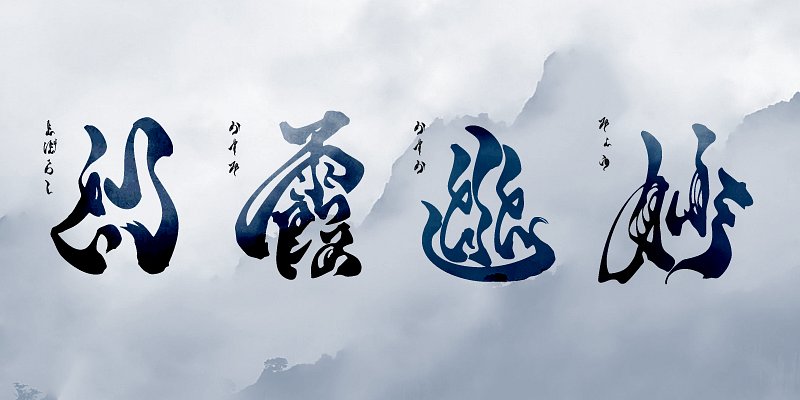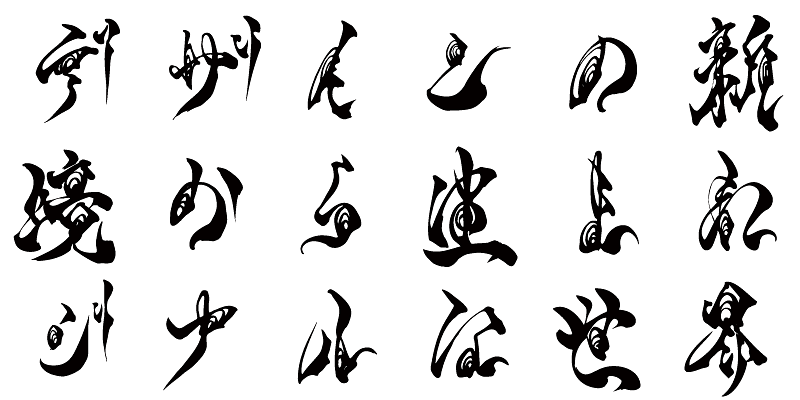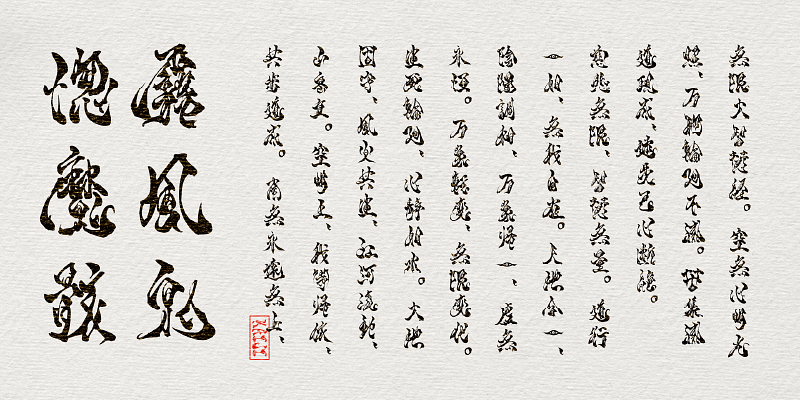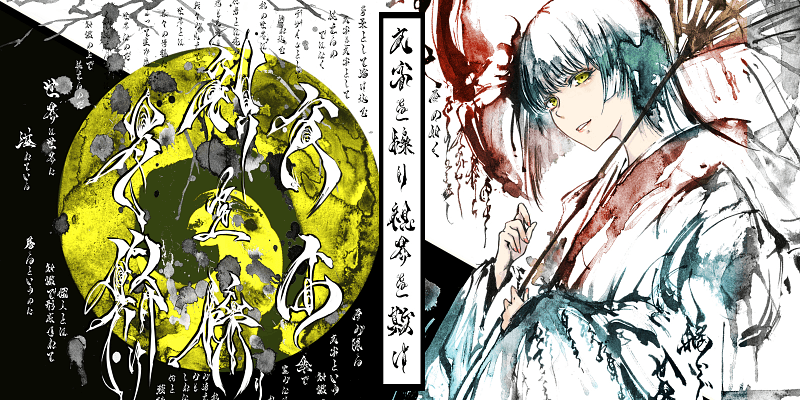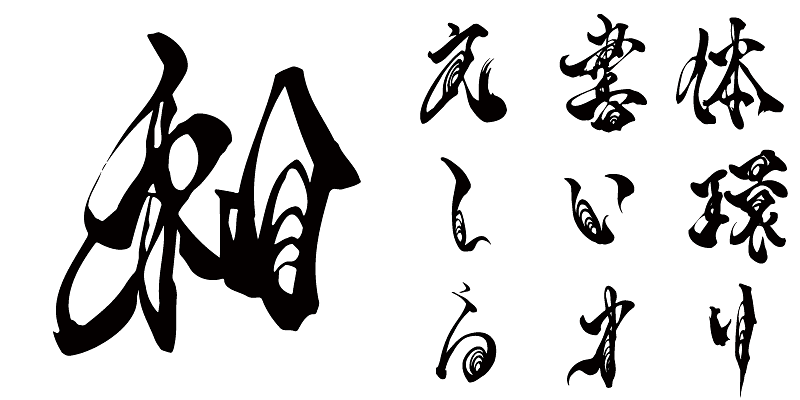
AB-kaij 서체의 문자는 바로 알아차릴 수 있지만 각 문자를 판독하는데 시간이 좀 걸립니다. 이 서체는 문자 그대로의 의미 이상을 전달할 수 있습니다. 이 서체를 사용하여 다양한 유형의 배경에 미러링 등과 같은 여러 이미지 효과를 적용할 수 있습니다.
이 글꼴 시리즈는 펜 캘리그래피를 바탕으로 2002년 출시된 오리지널 수기 일본어 서체를 포함하고 있습니다. 이들 글꼴은 그 따뜻한 시선으로 디자인의 핵심 포인트로 시선을 사로잡을 것입니다.